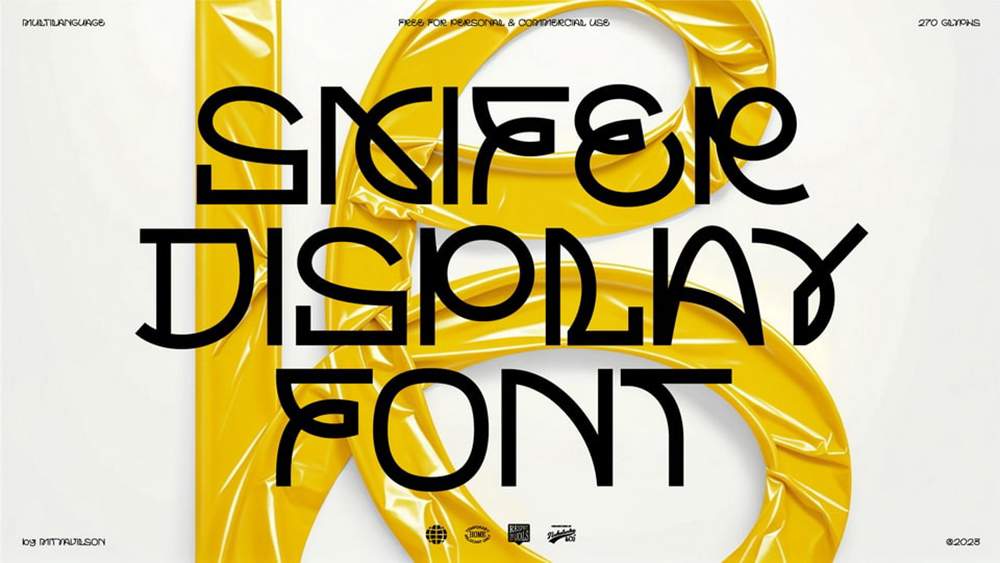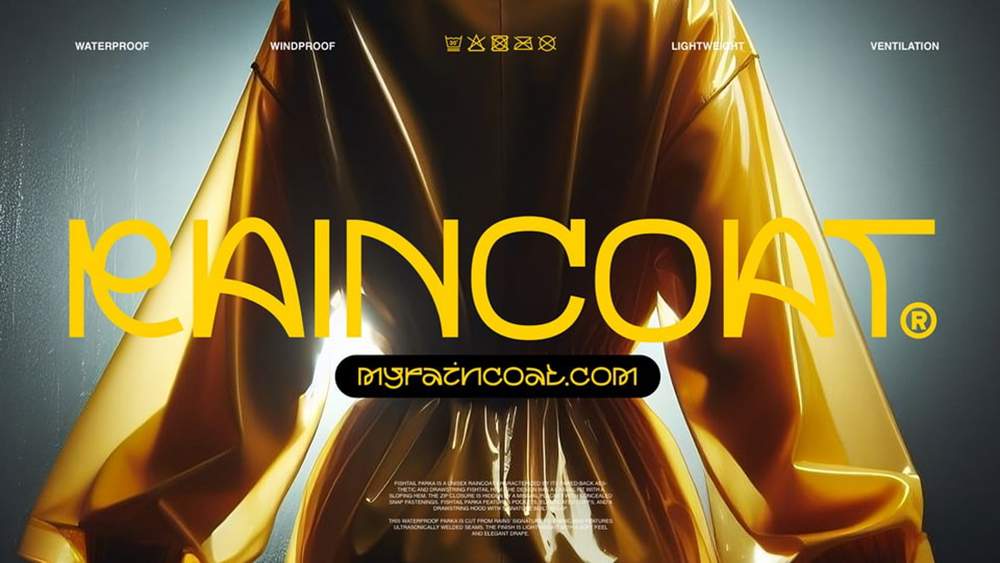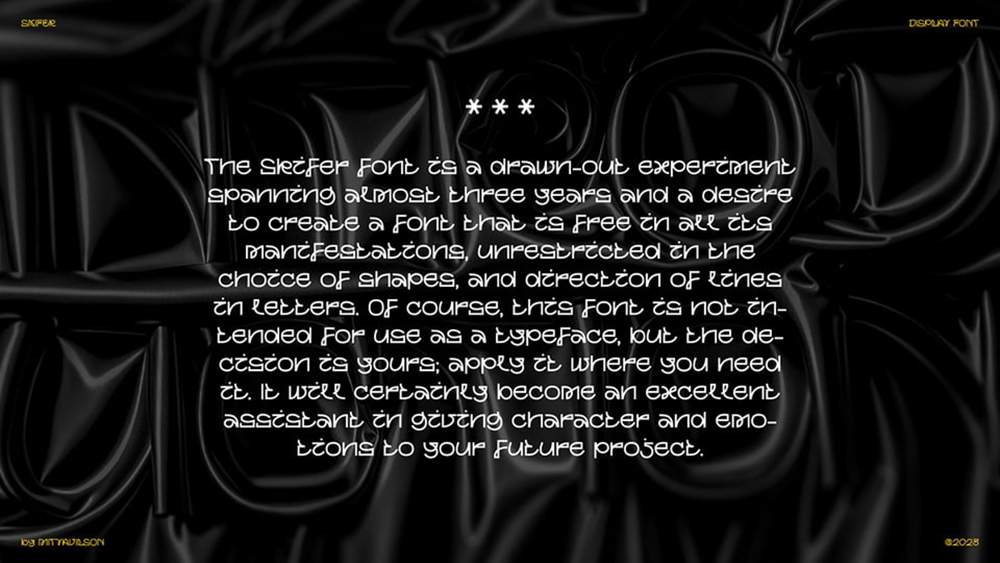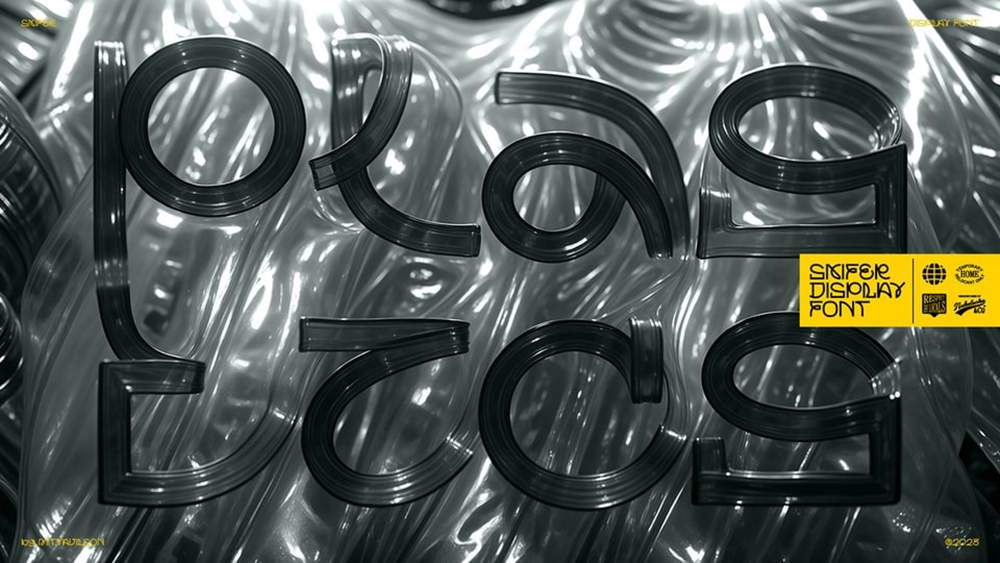
دانلود فونت انگلیسی MV-SKIFER Font
فونت پرمیوم و انگلیسی MV-SKIFER Font يک فونت آزمايشی کشيده است که در تمام جلوههای خود آزاد است و در انتخاب شکلها و جهت خطوط در حروف محدوديتی ندارد. البته، اين فونت برای استفاده به عنوان يک فونت در نظر گرفته نشده است، اما مطمئنا به يک دستيار عالی در شخصيت بخشيدن و احساسات بخشيدن به پروژه آينده شما تبديل خواهد شد. فونت MV-SKIFER که برای طرحهای آوانگارد، بيانيههای هنری و پروژههايی که نياز به خروج جسورانه از هنجار دارند، ايدهآل است، متن شما را به يک بوم نقاشی براي کاوش هنری تبديل میکند. ماهيت آزمايشی اين فونت، شما را به رهايی از تايپوگرافی سنتی دعوت میکند و به شما اين امکان را میدهد تا يک زبان بصری خلق کنيد که به اندازه خلاقيت، بیحد و مرز است.
مزایای استفاده از فونت لاتین MV-SKIFER چیست؟